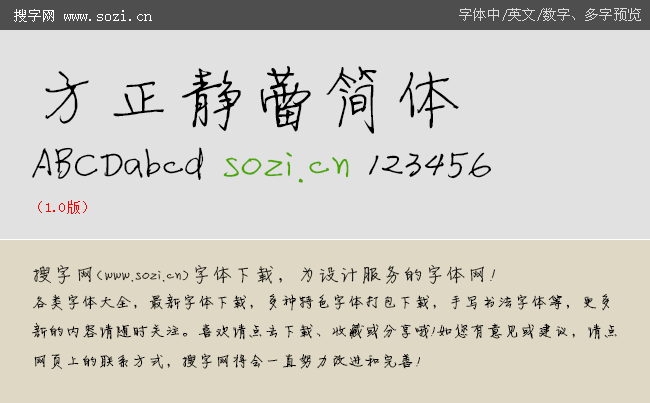
方正靜蕾簡(jiǎn)體(FZJLJW)
搜字網(wǎng)提供一款方正靜蕾簡(jiǎn)體下載,方正靜蕾簡(jiǎn)體是方正電子攜手徐靜蕾發(fā)布了其個(gè)人書(shū)法計(jì)算機(jī)字庫(kù)產(chǎn)品,字體骨骼清秀、遒勁有力,清冽而又優(yōu)雅、從容,令人賞心悅目。字如其人,心素如簡(jiǎn),人淡如菊。特別適用于書(shū)寫(xiě)信函、報(bào)告、文章等。
• 風(fēng)格類別: 手寫(xiě)書(shū)法體